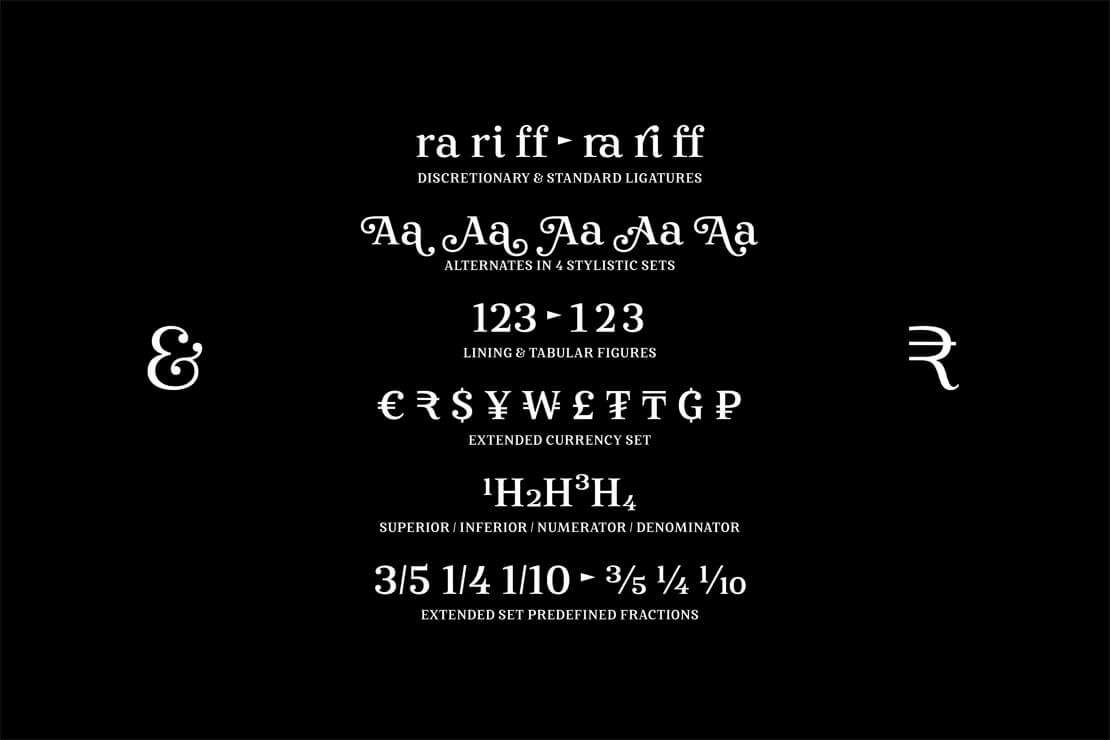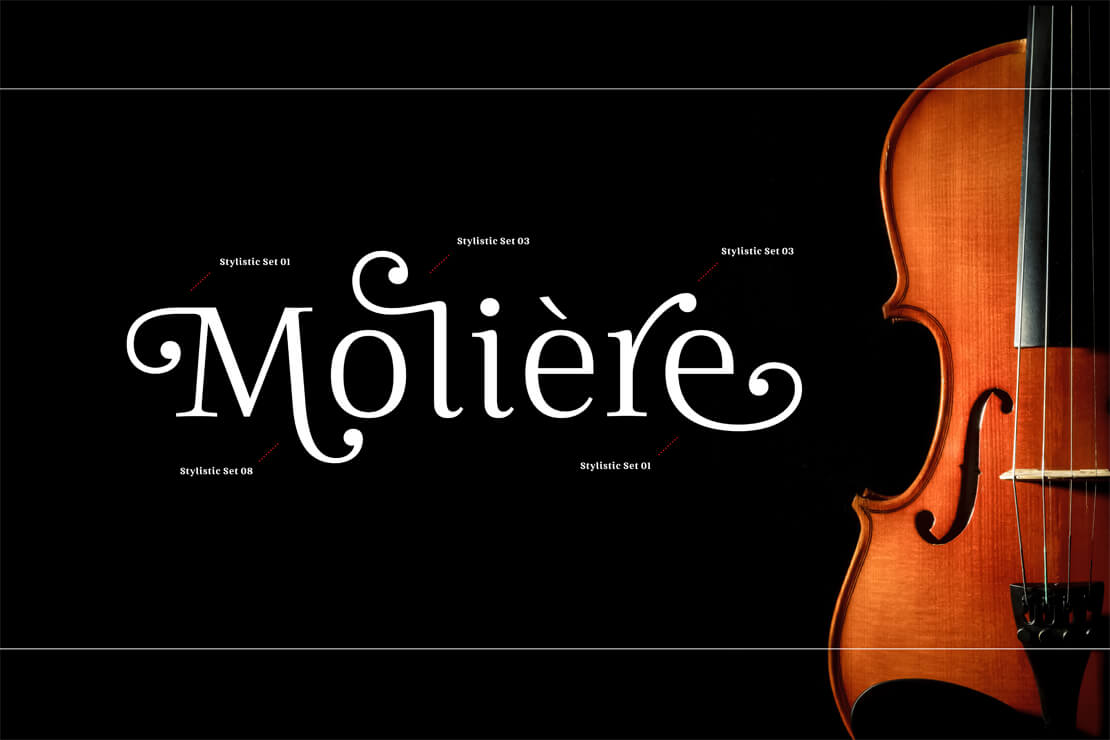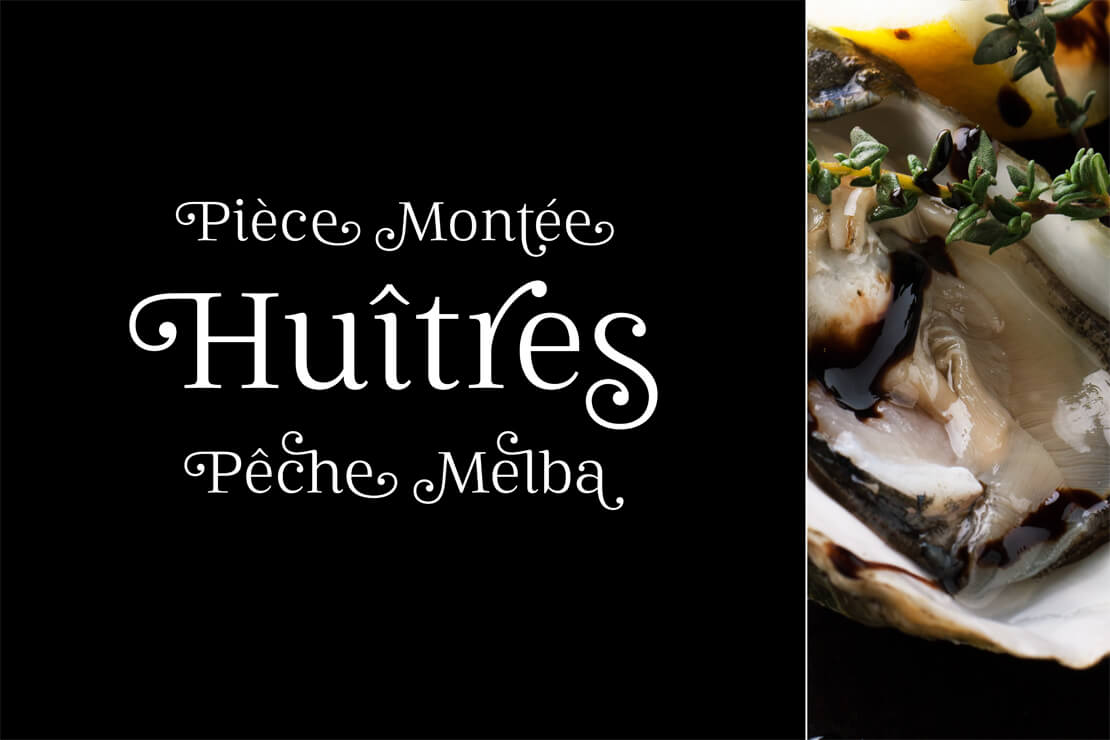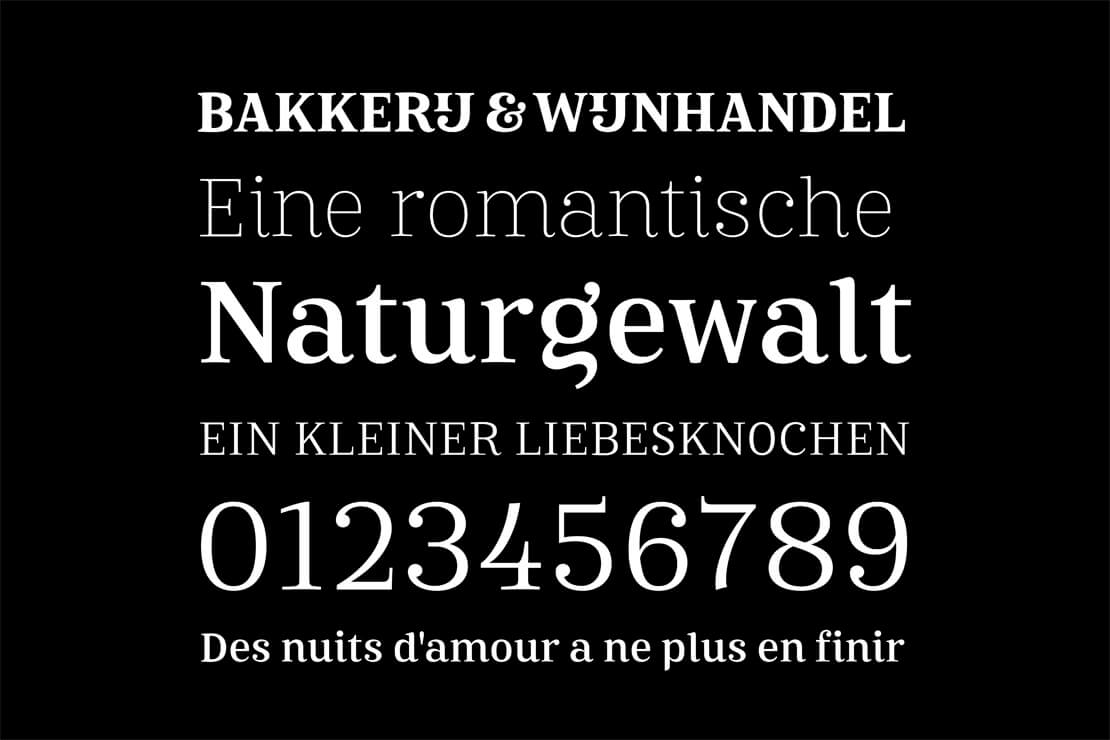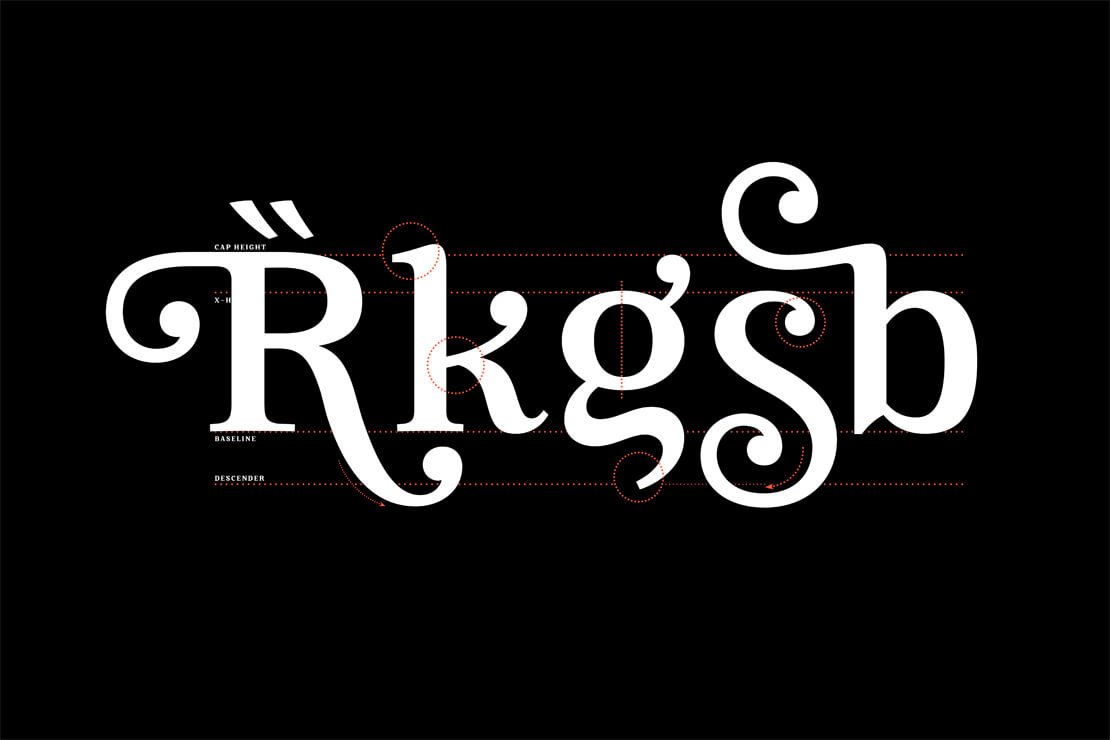
Mireille: Typografische Hommage an die französische Kultur
Anita Jürgeleit präsentiert ihre neue Schriftfamilie. »Mireille« ist eine typografische Hommage an die französische Kultur und enthält elegante Ligaturen sowie dekorative Alternate-Buchstaben.
Mit 7 Schriftschnitten bietet »Mireille« kreativen Spielraum für Branding, Poster, Buchcovers und Headlines – beispielsweise in Bereichen wie Restaurants oder Kulturhäuser.
Die Schriftfamilie von Anita Jürgeleit kommt mit über 100 Ligaturen und dekorativen Zeichen. Über 1.000 Glyphen bedienen alle europäisch-lateinischen Sprachen. Die zusätzlichen 4 Stylistic-Sets verfügen zudem über alternative Zeichen, Ligaturen und erweiterte Nummern- und Währungssets.